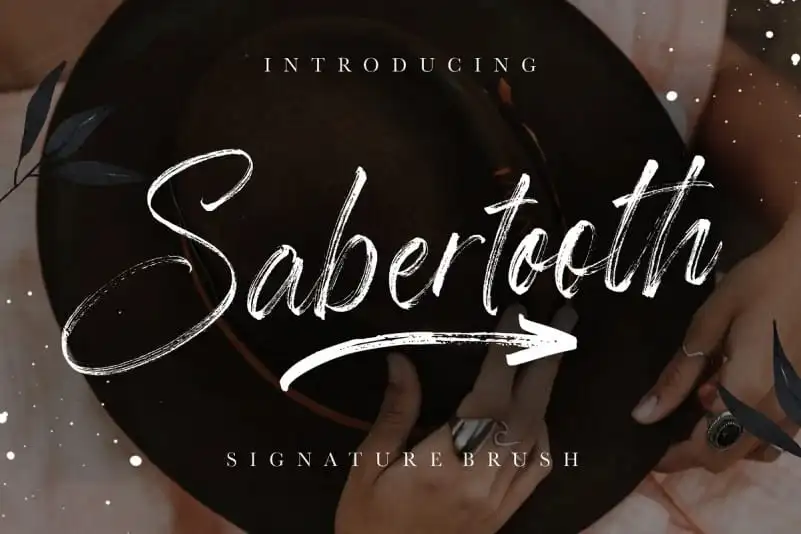
Sabertooth Brush Font é uma tipografia script casual e rápida, criada para quem busca personalidade única em seus projetos digitais. As letras são feitas com pincéis no papel e seu design elegante e versátil faz dele um recurso perfeito tanto para a criação de marcas e logotipos quanto para o desenho de produtos e embalagens. Sabertooth é ideal para trabalhos que exigem um toque autêntico da mão, como cartões de visita, materiais de escritório, anúncios e postagem nas redes sociais. Seja qual seja seu projeto, sabemos que Sabertooth tem uma solução perfeita para você. Este é o recurso gráfico que tanto precisava em sua arsenal de ferramentas digitais.